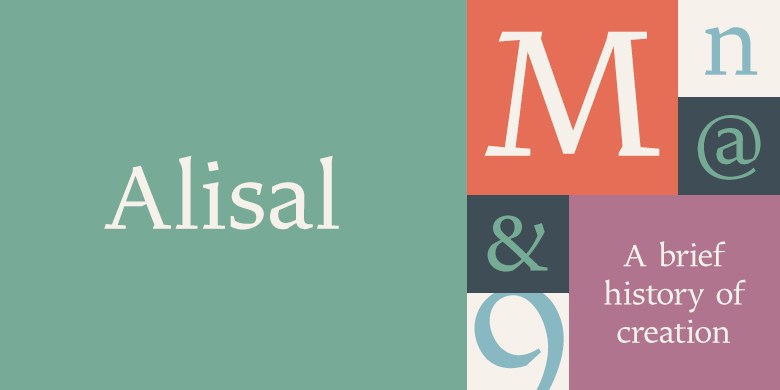
Matthew Carter说,他一直在完善Alisal的设计,以至于当他被要求来完成Monotype Library的设计时,感觉就像是在对自己的字体进行历史性的复刻一样。这种感觉甚至延伸到他的工作过程中的变化:尽管他现在已经在屏幕上完成了所有初始版本和最终版本的绘制,但Alisal的第一个试用版效果图是用铅笔完成的。
Alisal最适合归类为意大利老式设计。真正的意大利老式风格最早出现于15世纪末至16世纪中期的意大利北部,是最早的罗马风格。它们往往是衬线字体中最具书法特色的,其弯曲笔画的轴线向左倾斜,像是用平头的笔或笔刷绘制的一样。这些设计具有坚固、流畅且明显弯曲的衬线,下伸部较短且笔画粗细对比适中。
Alisal几乎拥有所有经典的意大利老式风格特征,再加上自己的一些怪异的特点。它本质上是书法的,比诸如Palatino或Goudy Old Style之类的字体更像是钢笔绘制的。它比Goudy的Kennerley或Benton的Cloister更粗糙,而且字重通常比其他大多数意大利老式设计要粗。Alisal与传统的老式设计完全不同的地方是衬线。虽然粗狂且清晰地反映了钢笔绘制笔画,但Alisal的衬线没有弯曲,并且看起来像是直笔画相交于垂直主笔画。
与Caslon或Trajanus一样,当把Alisal看作是一件复制品时,它是一个漂亮的设计。上伸部既高大又优雅,可以与其余设计相提并论。 Alisal是一个包含罗马体和粗体的小型家族,还有一个基本罗马字重的补充斜体,提供了大多数文本排版所需的全部内容。
Alisal并不像Carter的其他字体那样广为人知,但这个可爱且酝酿已久的设计绝对值得期待。
Matthew Carter has been refining his design for Alisal for so long, he says, that when he was asked to complete the design for the Monotype Library, it was almost as if he were doing a historical revival of his own typeface. The illusion even extended to changes in his work process: although he now does all his preliminary and final drawing on screen, the first trial renderings of Alisal were done as pencil renderings.
Alisal is best classified as an Italian old style design. Originally created between the late 15th and mid-16th centuries in northern Italy, the true Italian old styles were some of the first roman types. They tend to be the most calligraphic of serifed faces, with the axis of their curved strokes inclined to the left, as if drawn with a flat-tipped pen or brush. These designs offer sturdy, free-flowing and heavily bracketed serifs, short descenders, and a modest contrast in stroke weight.
Alisal has nearly all the classic Italian old style character traits, plus a few quirks of its own. It is calligraphic in nature, with more of a pen-drawn quality than faces like Palatino or Goudy Old Style. It is more rough-hewn than either Goudy’s Kennerley or Benton’s Cloister, and is generally heavier in weight than most of the other Italian old style designs. One place where Alisal makes a clean break with traditional old style designs is in the serifs. While sturdy and clearly reflecting pen-drawn strokes, Alisal’s serifs have no bracketing and appear to be straight strokes crossing the main vertical.
Like Caslon or Trajanus, Alisal is a handsome design when viewed as a block of copy. Ascenders are tall and elegant, and serve as a counterpoint to the robust strength of the rest of the design. Alisal is available as a small family of roman and bold with a complementary italic for the basic roman weight, providing all that is needed for the majority of text typography.
Alisal is not as well-known as some of Carter’s other typefaces, but this lovely and long-incubated design was certainly worth the wait.